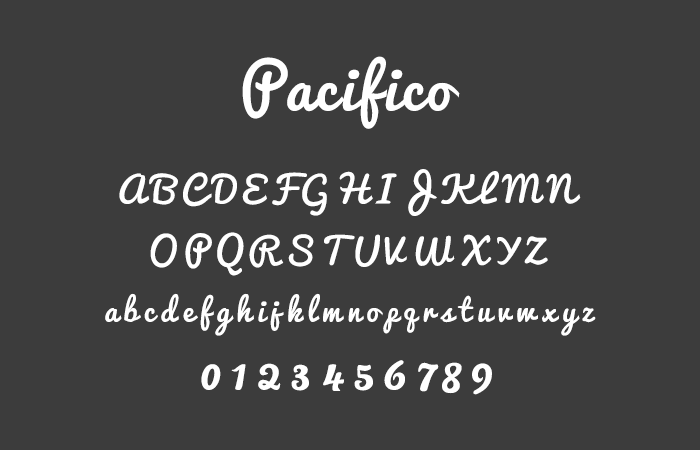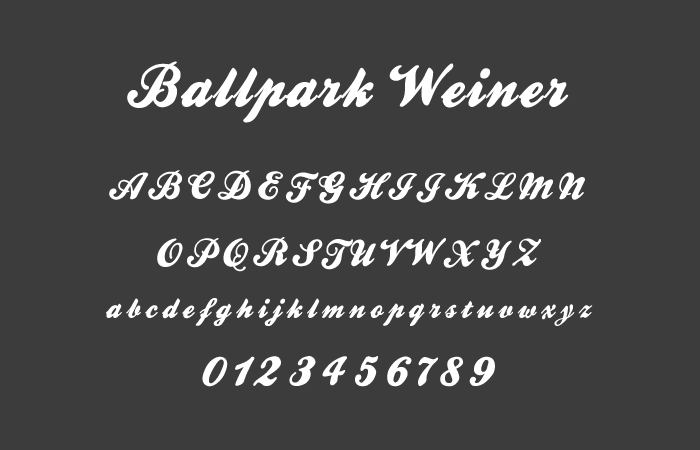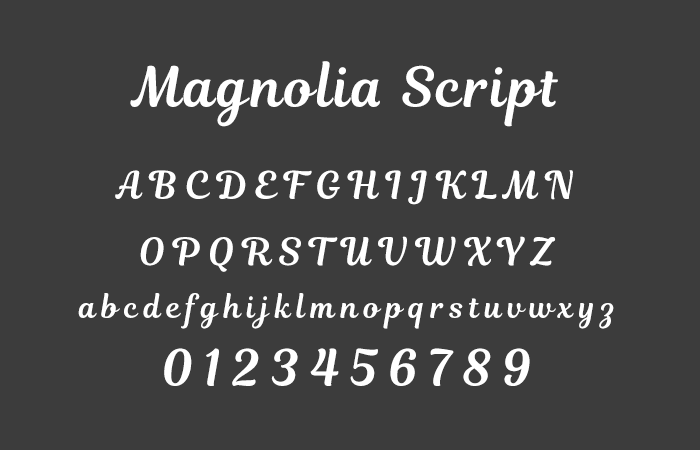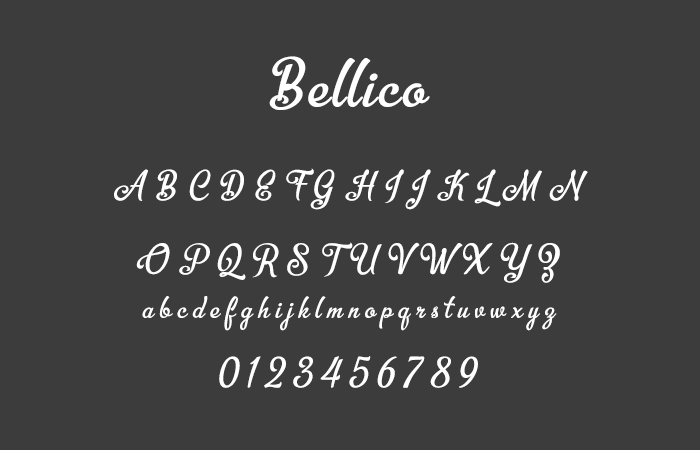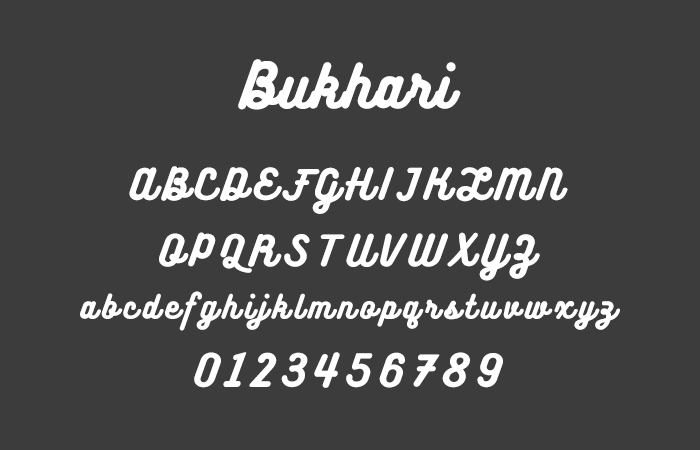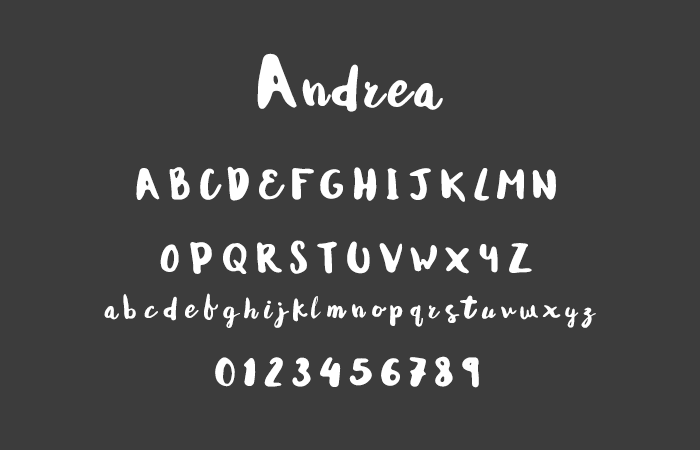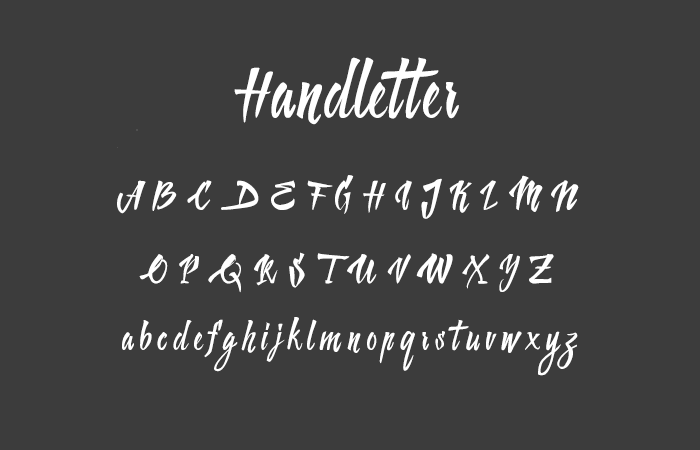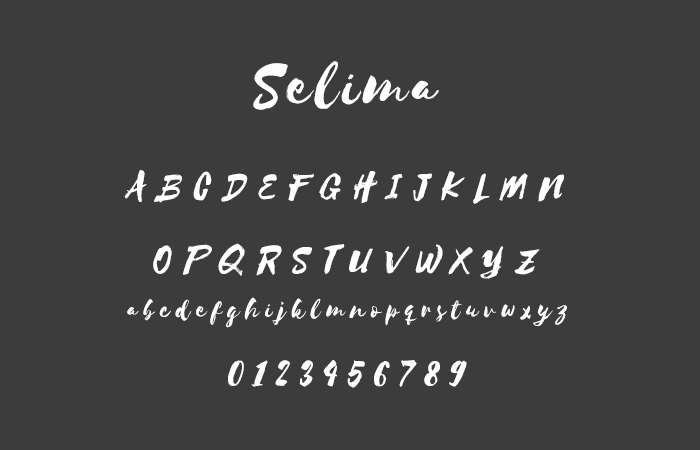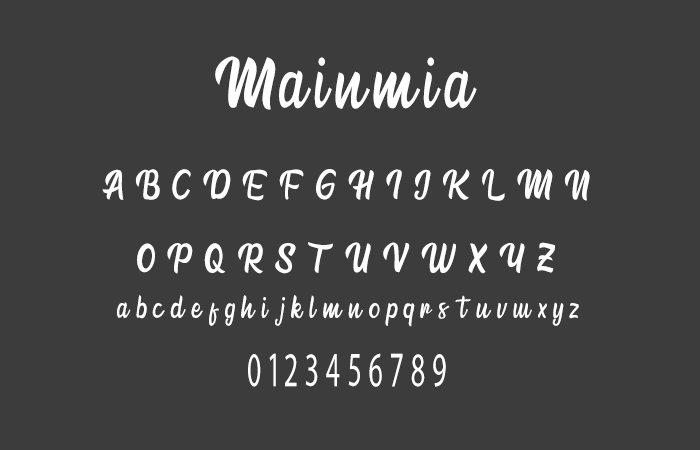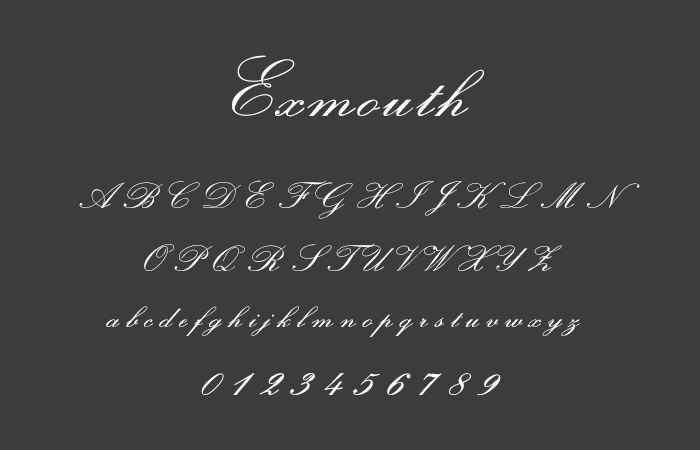
無料で使えるおしゃれな英語の筆記体フリーフォント20選
流れるような手書き感のある筆記体フォントはバリエーションが豊富で人気の書体です。オーソドックスなタイプから、ポップなタイプまで無料でダウンロードできる英語の筆記体(Script)フォントを紹介します。
細字 (Fine Script)
That’s Font Folks!
Henry Morgan Hand
Buffalo
Restless
太字 (Bold Script)
Ballpark Weiner
Magnolia Script